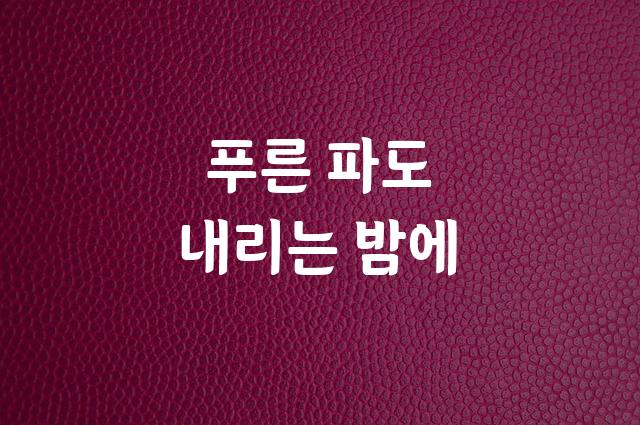
영덕대게체는 영덕군에서 제작한 제목용, 장식체 폰트로, 둥근 고딕 스타일이 특징입니다. 귀여운 느낌과 뿔 모양의 유니크한 디테일이 돋보이는 디자인입니다.
영덕대게체은(는)
길고/크고, 기본 고딕, 별모양/패턴, 복실복실, 부드러움, 자연감성, 감성적인, 장식 스타일, 꼬임/입체감, 귀여운 스타일, 둥근 스타일 계열의 생김새를 가지고 있으며
소셜 미디어, 카페 메뉴, 광고 캠페인 등에서 자주 활용되며, 효과적인 메시지 전달에 적합합니다.
이 폰트는 관광/여행, 라이프스타일, 음식/식음료 분야에 잘 어울리며,
자연스러운, 편안한, 친근한 느낌을 담고 있는 것이 특징입니다.